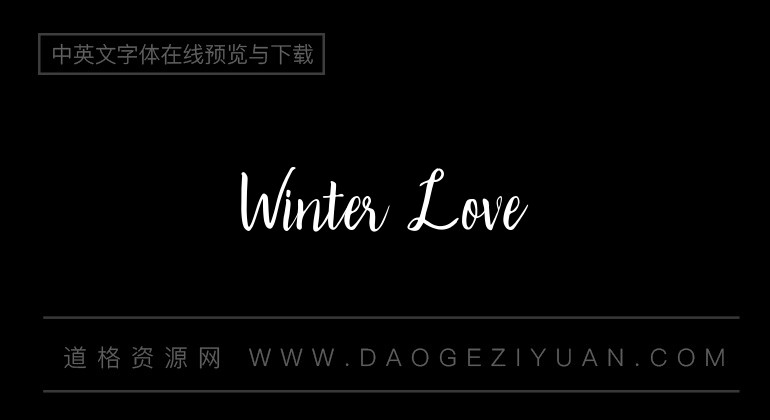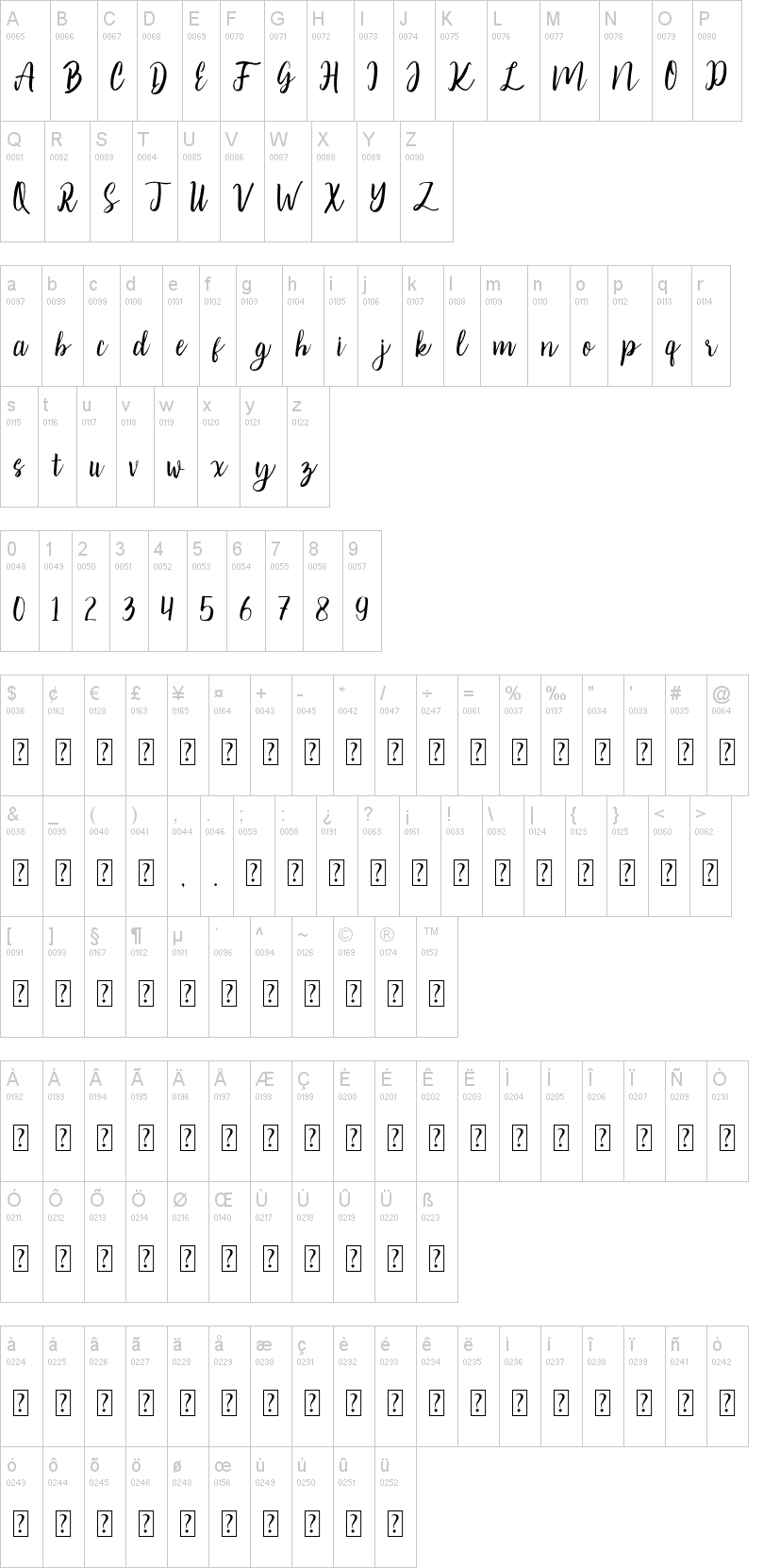
Winter Love字体是由英国设计师Laura Worthington设计的一款手写体字体。它特别适合制作浪漫的节日卡片、礼品标签和婚礼邀请函,具有精致的手写风格,温暖的气息,令人感受到温馨的浪漫气氛。它有两种字体风格,一种是普通的斜体,另一种是带有古典风格的斜体。它非常适合用来制作浪漫的节日卡片、礼品标签和婚礼邀请函,可以使这些作品更加具有浪漫的气息。内容介绍
Winter Love是一款非常不错的手写艺术字体,具有很好的视觉感,适合于文化类的宣传设计、商业类品牌的广告和产品包装设计以及个性化文字排版等较多场景。